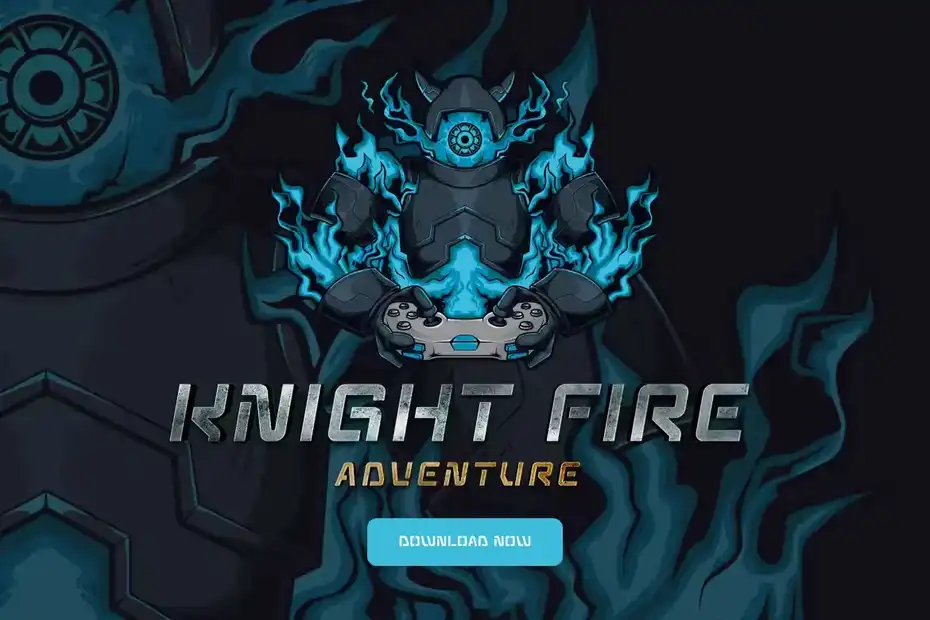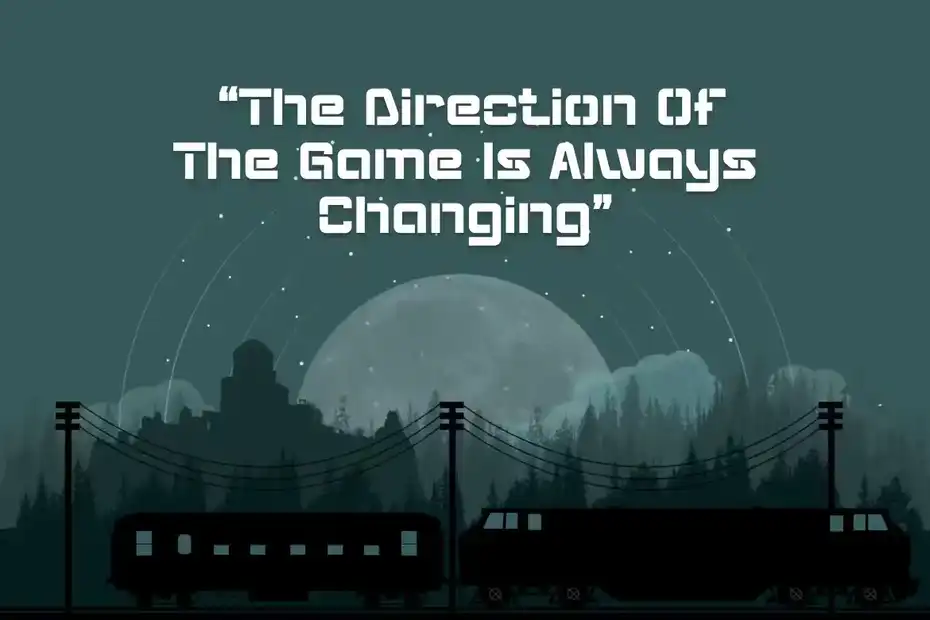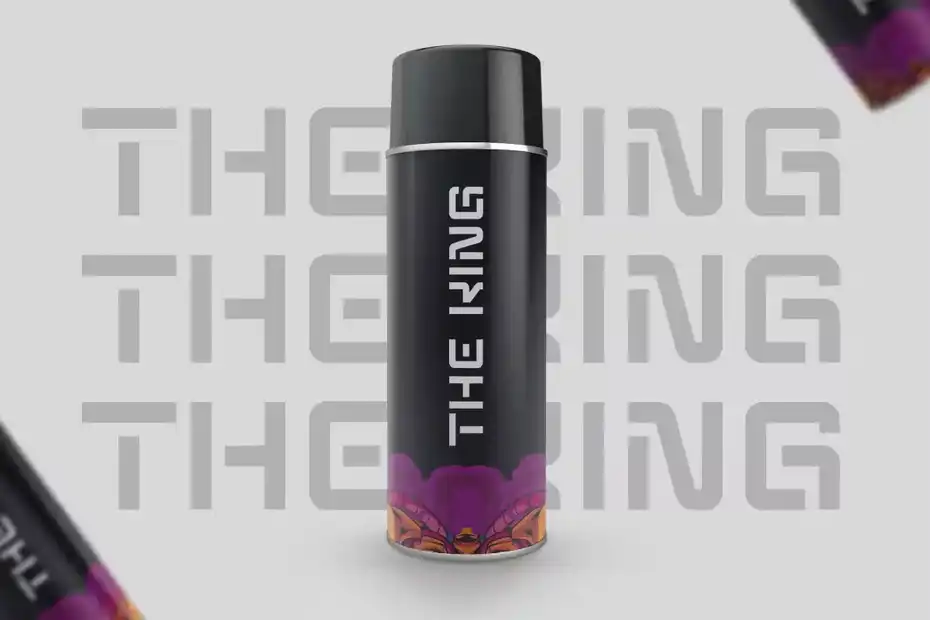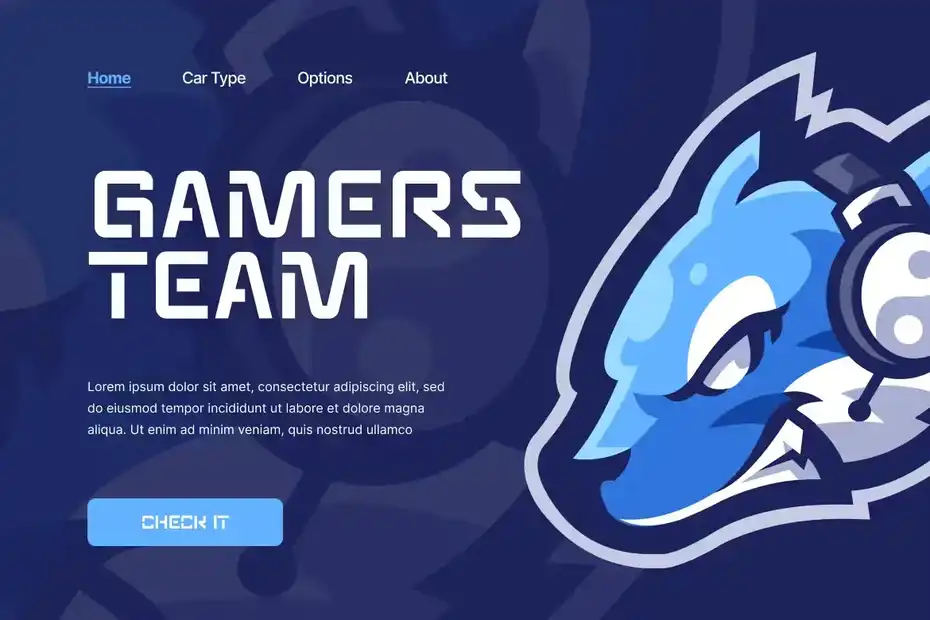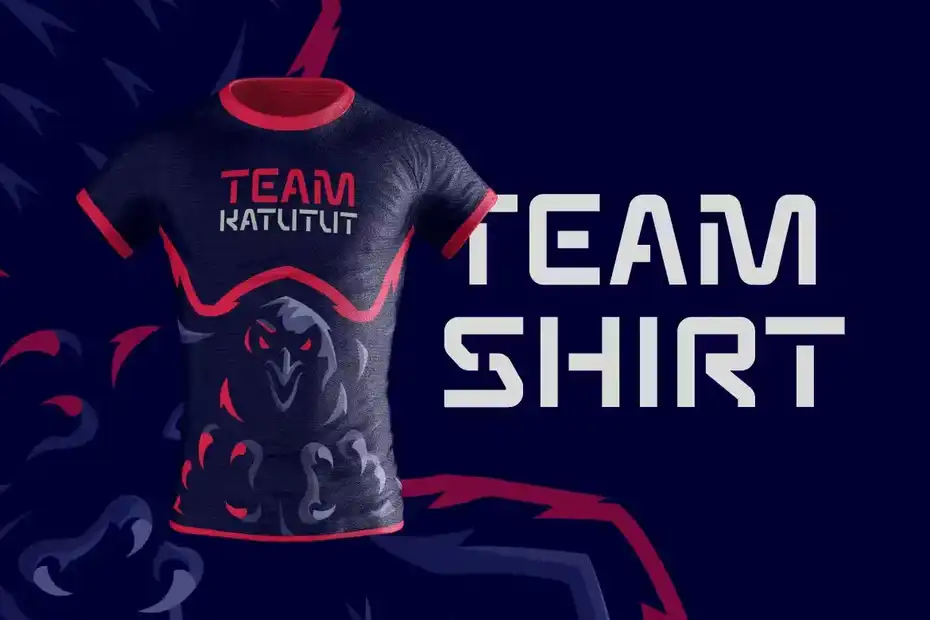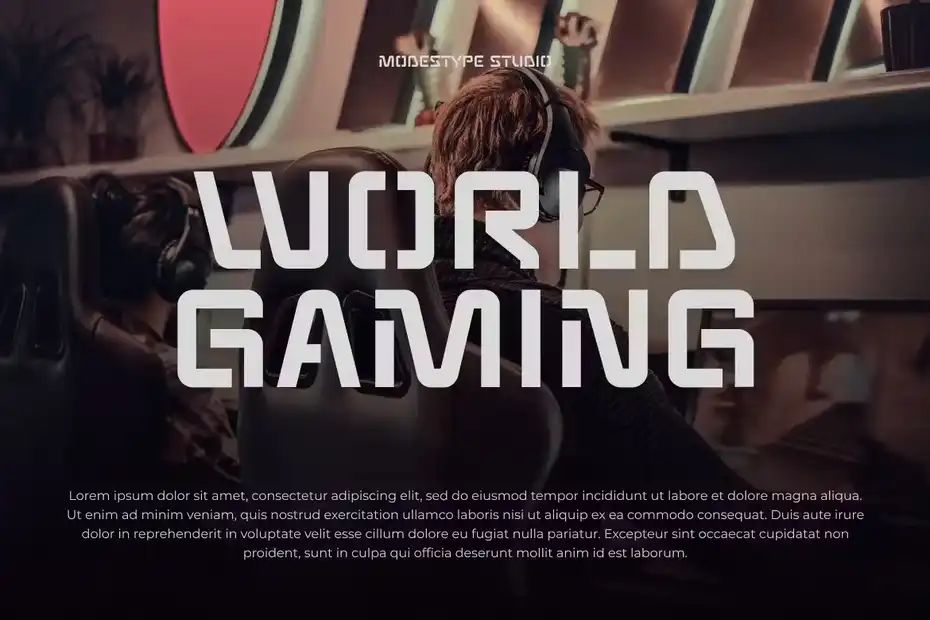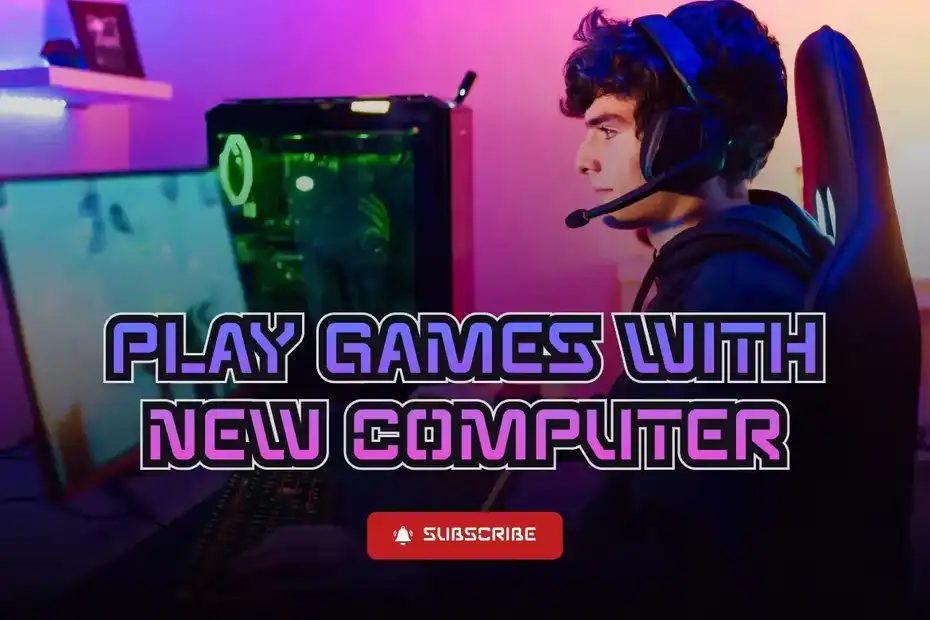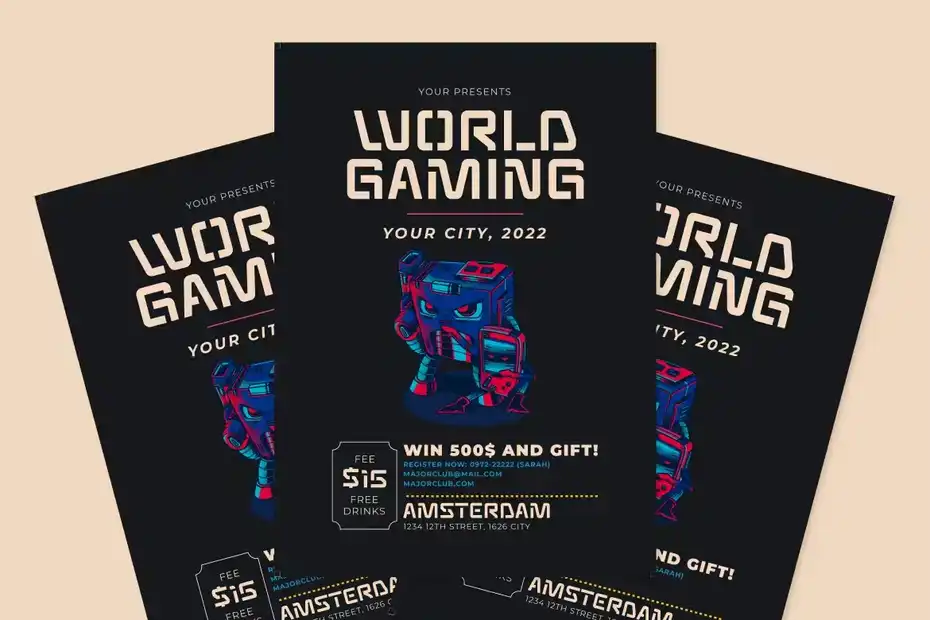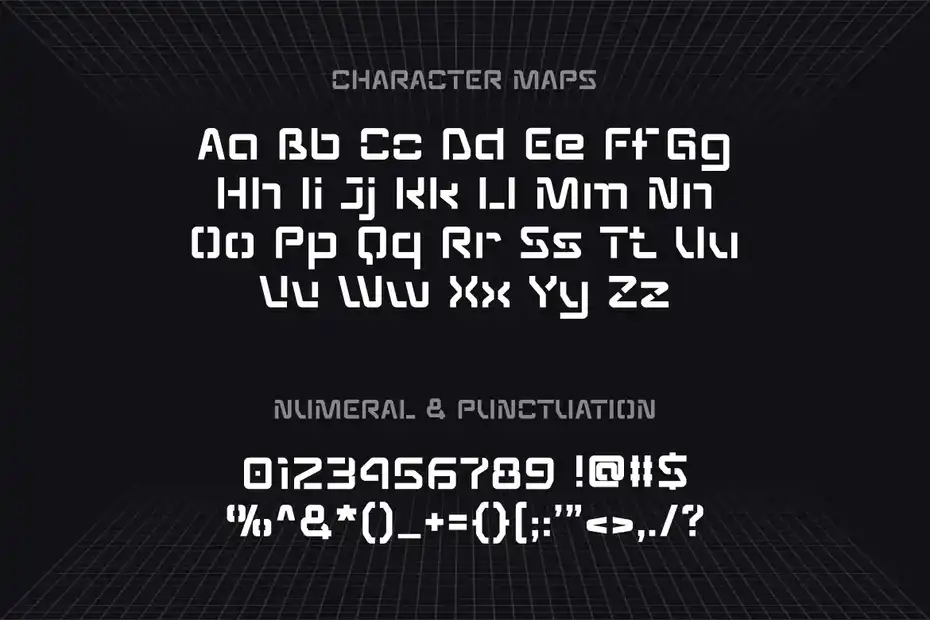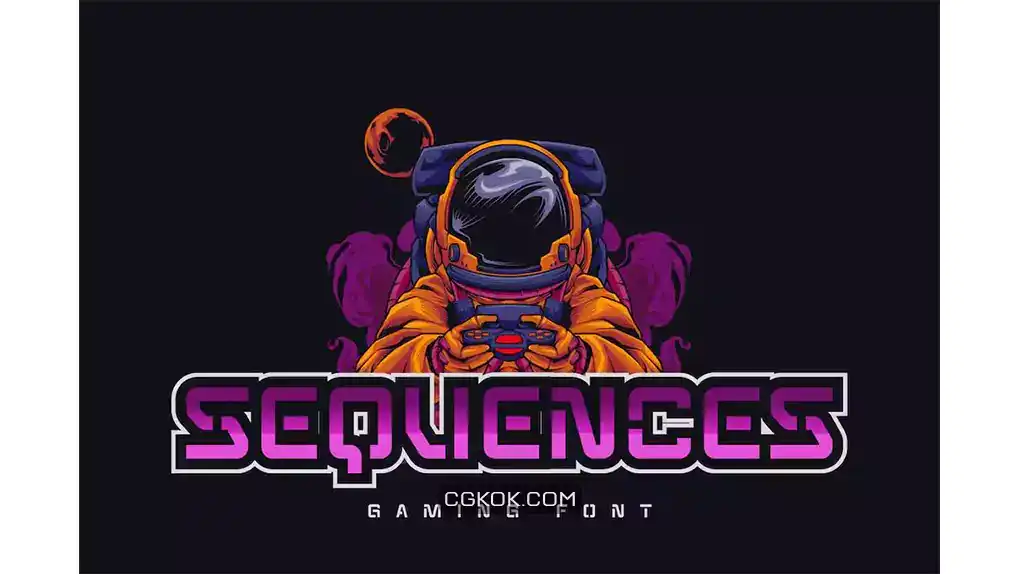
دانلود فونت انگلیسی گیمینگ SEQUENCES – Gaming Font
فونت انگلیسی گیمینگ SEQUENCES – Gaming Font : این مجموعه شامل یک فونت انگلیسی مدرن است که برای بازی، مجله علمی تخیلی، پوستر، عنوان فیلم، پوستر موسیقی، کاور یوتیوب، تصاویر کوچک یوتیوب، کاور شبکه های اجتماعی و غیره مناسب میباشد.